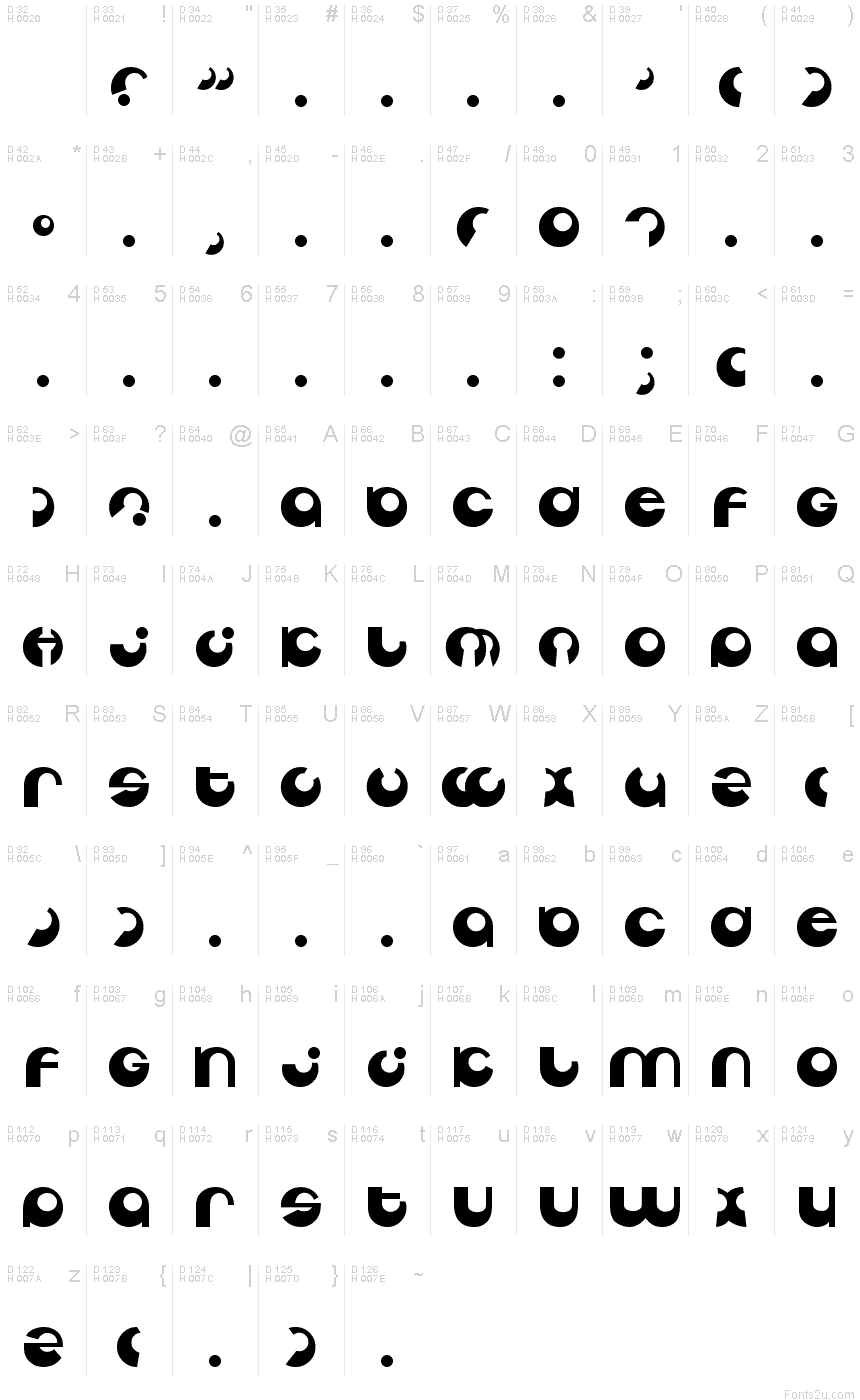
Tabun od Barmee to darmowy, groovowy font typu display, który oddaje klimat końcówki lat 60. – jest miękki, obły i pełen energii. Litery zbudowane są z szerokich, zaokrąglonych kresek i wyrazistych krzywizn, które są jednocześnie ściągnięte nagłymi płaskimi cięciami i wąskimi łączeniami. Dzięki temu font zyskuje figlarną dynamikę, daleką od nudnej, geometrycznej statyki.
Świetnie sprawdzi się na plakatach, w oprawie muzycznej, brandingu kawiarni, zinach i tytułach, wszędzie tam, gdzie retro-popowy rytm gra pierwsze skrzypce. Jako darmowy font, Tabun najlepiej wypada w krótkich frazach i wyrazistych nagłówkach – jego zwarte łączenia i duże, obłe kształty nadają nawet prostym słowom niezwykle mocną sylwetkę.
Tabun